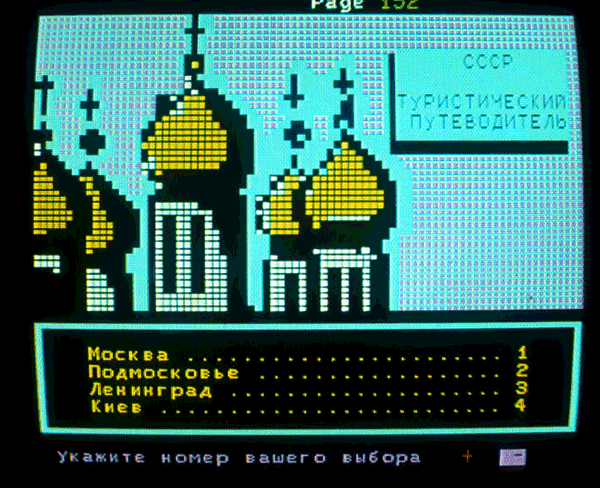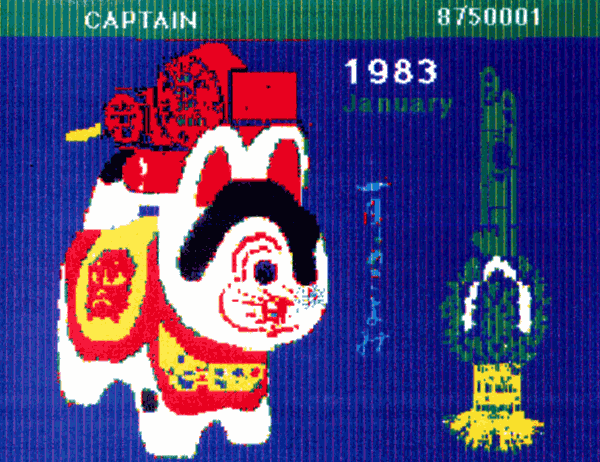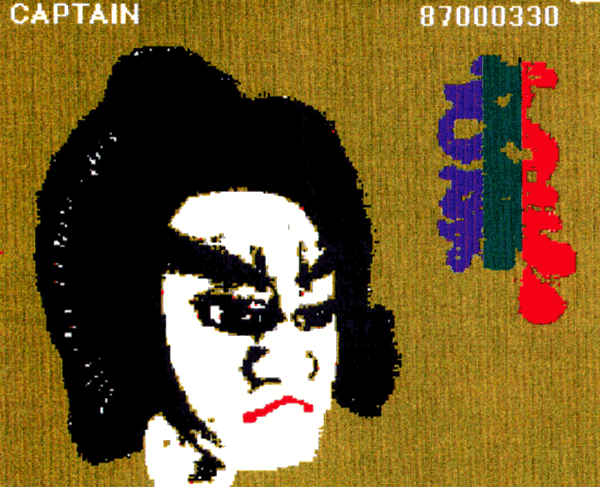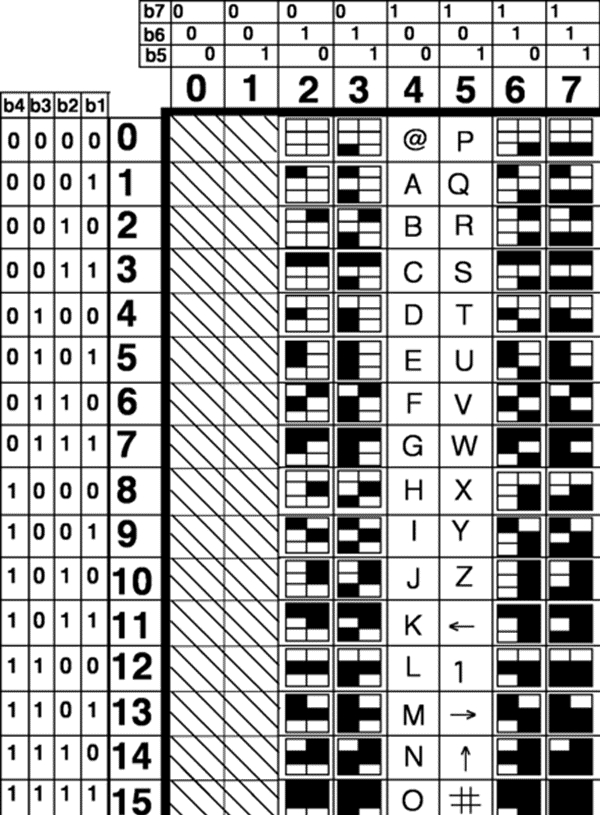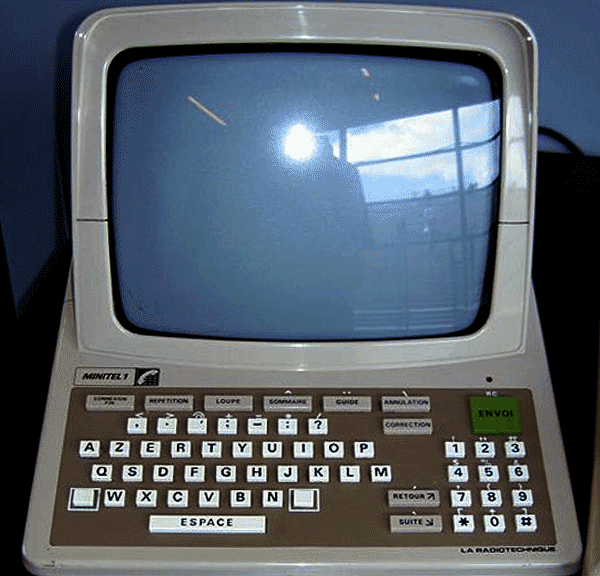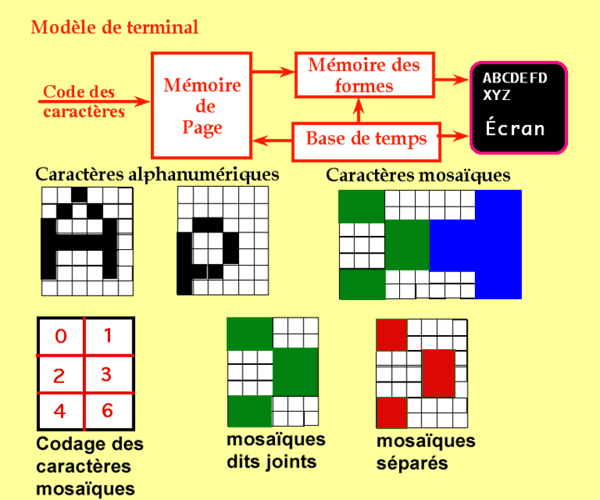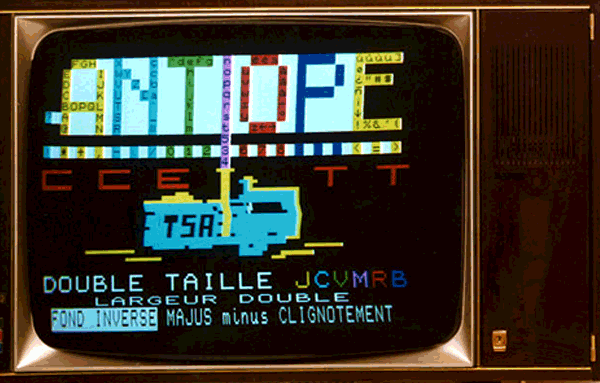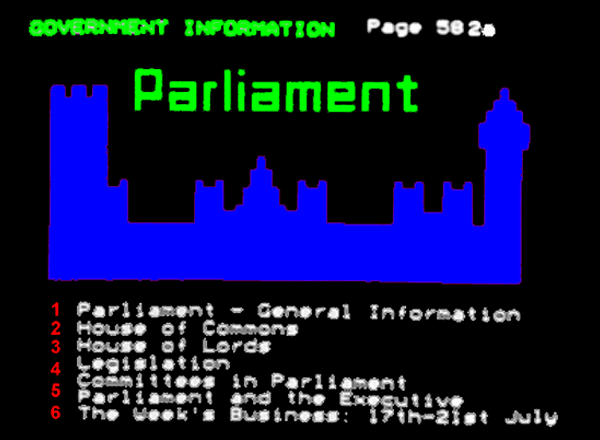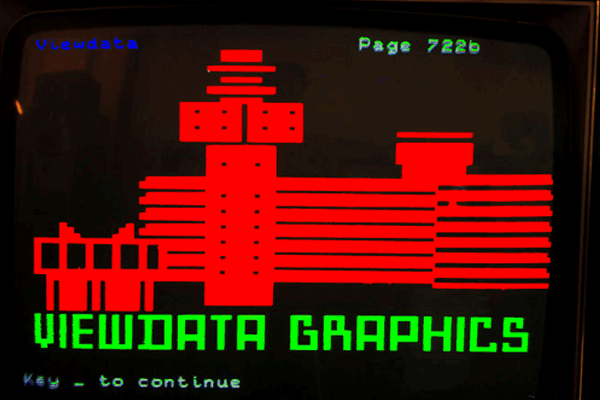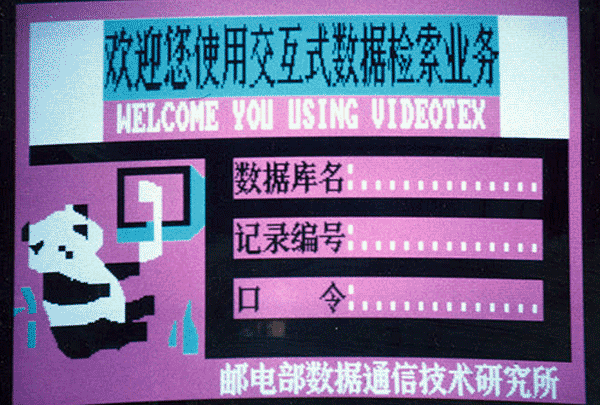
DaDa le minitel? bien involontairement oui!
Entre 1970 et 1978 la France met au point le protocole de communication du minitel qui anticipe dans les années 80 sur le réseau des trois W. Basé sur l’échange de données analogique via le téléphone, celui-ci n’autorise aucune nuance pour l’affichage des images. Nous sommes loin du PostScript et du WYSIWYG qui va déferler à la fin des années 80. L’expression ‘telematique’ va donner lieu à un style graphique minimaliste qui n’est pas sans rappeler l’expression des jeux vidéos de l’époque (pong, atari etc.). Mais aussi bien que la typographie russe des années vingt. Le signe ‘bitmap’ vient de naître et nous rappelle une fois de plus que bien souvent la technologie est à l’origine des inventions du design graphique. De nombreux graphistes et typographes vont trouver là un mode d’expression des plus intéressants… j’espère que Jonathan va réagir pour commenter ce billet, puisqu’il a participé personnellement à cette phase extrêmement importante de la bascule de Gutenberg vers la typographie virtuelle.
Connaissez-vous le travail que j’ai mené (Frédéric develay et Orlan) avec ART ACCES REVUE dès 1985 ?
4.2.1 La revue télématique Art-Acces
Le minitel joue un rôle important dans la naissance de la poésie animée française Ö car la plupart des auteurs français de cette mouvance ont publié ensemble dans la revue Art-Acces, l’unique revue télématique qui vit le jour. Y ont participés, en tant que critique, Jean-Pierre Balpe, et, en tant qu’auteurs, Philippe Bootz, Frédéric Develay, Claude Faure, Guillaume Loizillon, Tibor Papp. Tous, hormis Jean-Pierre Balpe, sont alors dans la mouvance des poésies visuelles et sonores et joueront un rôle déterminant dans l’évolution de la poésie numérique française.
Art-Acces a été créée en France en 1985 par Orlan et Frédéric Develay. Cette revue était généraliste. Trois numéros seulement ont été réalisés car elle était totalement dépendante du bon vouloir de France Telecom qui détenait l’ensemble du réseau télématique et des moyens de production. Le premier numéro, le numéro 0, a été réalisé pour l’exposition Les Immatériaux qui s’est tenue au Centre Pompidou cette année-là Ö. Les Immatériaux est une exposition très importante dans l’histoire de la littérature numérique française car elle fut la première exposition d’art numérique en France à montrer les aspects de la littérature numérique française de cette époque, à savoir l’animation de texte, présentée sur minitel, et la génération automatique de Jean-Pierre Balpe Ö.
Le numéro 1 d’Art-Acces a pu être consulté sur tout minitel à partir de 1985. Il comprenait 500 pages écrans. Le numéro 2 a été réalisé en 1986.
Voici comment les concepteurs de la revue la présentent
« Réalisation par des plasticiens, des compositeurs et des écrivains contemporains d’œuvres originales conçues pour le vidéotext, et encadrées de deux textes à fonction didactique :
– l’un écrit par l’artiste ou l’auteur, et donnant son angle d’attaque du média
– l’autre écrit par un critique du choix de l’artiste, et donnant des points de repères concernant son trajet » [9]
La télématique a permis de mettre en place une première esquisse des animations syntaxiques Ö par le fait que plusieurs pages pouvaient être liées et que les clignotements étaient possibles. Elle a également permis de travailler pour la première fois les effets de tension sur la lecture qu’amène l’interactivité. En effet, la communication téléphonique étant payante et le minitel étant lent, le public pouvait être tiraillé à chaque page écran entre abandonner et continuer la lecture. Par exemple, mon TEXT (Philippe Bootz, 1986) comportait 8 pages-écrans dont 3 étaient liées. Voici le commentaire qui l’accompagnait.
« Les engrenages de mots engendrent plus d’information que n’en peut contenir un texte. Dans cette imbrication des supports (langue, position, typographie, couleur), chaque accident est signifiant, y compris les transitoires entre deux pages. Qu’importe d’ailleurs cette surabondance, la difficulté pour comparer deux pages entre elles, la distorsion des couleurs et l’obligation de recourir à des transitoires favorisent une lecture destructive/créative où le texte se plie au lecteur. » (BOOTZ Philippe, « présentation de TEXT », Art Acces n°2, 1986)
Il montre que sont déjà travaillées à cette occasion certaines questions approfondies plus tard en poésie programmée animée comme le rôle pivot du transitoire observable Ö, la difficulté de lecture, l’approche de la lecture comme destruction/création. Ces conceptions, centrales dans toute l’animation programmée développée ultérieurement au sein de la revue alire Ö sont déjà en germe dès le milieu des années 1980.